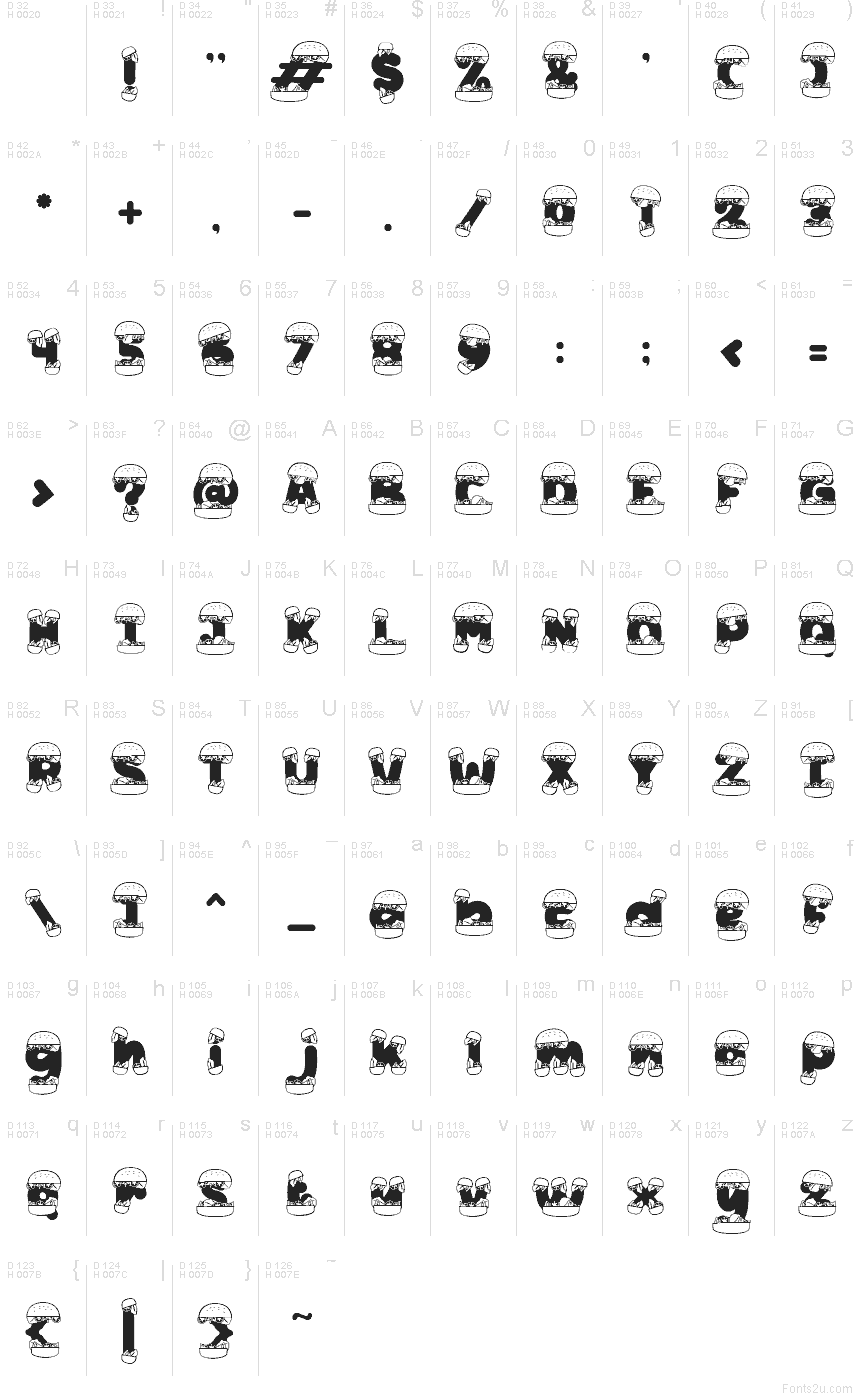
Smoky Maple Three de Putracetol Studio es una tipografía display kawaii gratuita, ideal para diseños relacionados con la comida. Su estilo cartoon lúdico se basa en formas redondeadas, bordes que chorrean y bases que recuerdan a cuencos. Las letras parecen personajes animados más que simples formas, combinando siluetas robustas con pequeños detalles faciales y acentos que parecen adornos, dando a toda la fuente un aspecto alegremente peculiar.
Es perfecta para branding de snacks, packaging infantil, carteles de cafeterías, portadas de YouTube y títulos cortos donde una fuente gratuita puede transmitir toda la atmósfera por sí sola. Úsala para nombres, logotipos, encabezados de menús o iniciales tipo monograma cuando quieras que las letras se lean como delicias ilustradas en lugar de una tipografía estándar.
Smoky Maple Three